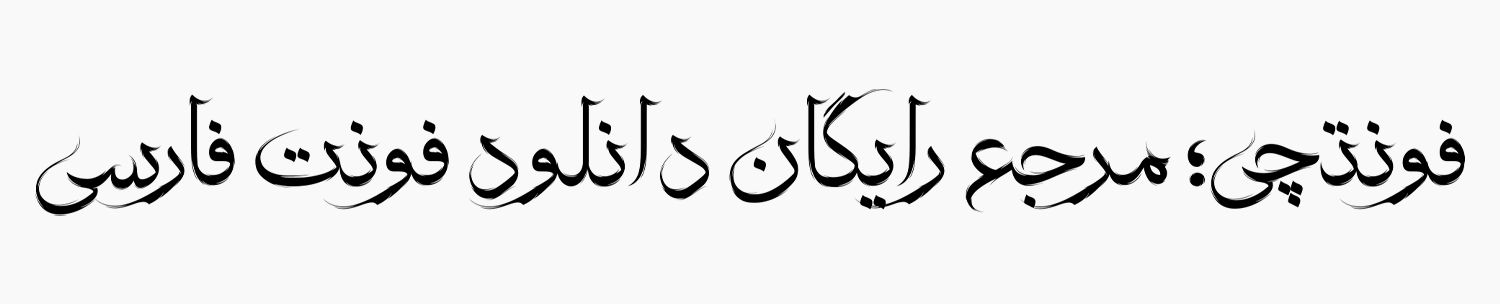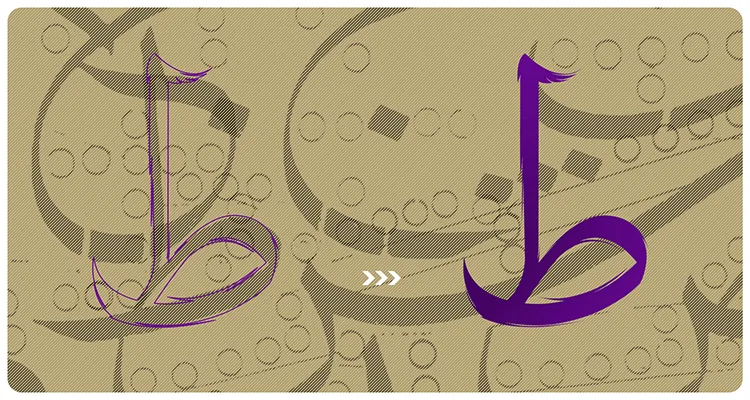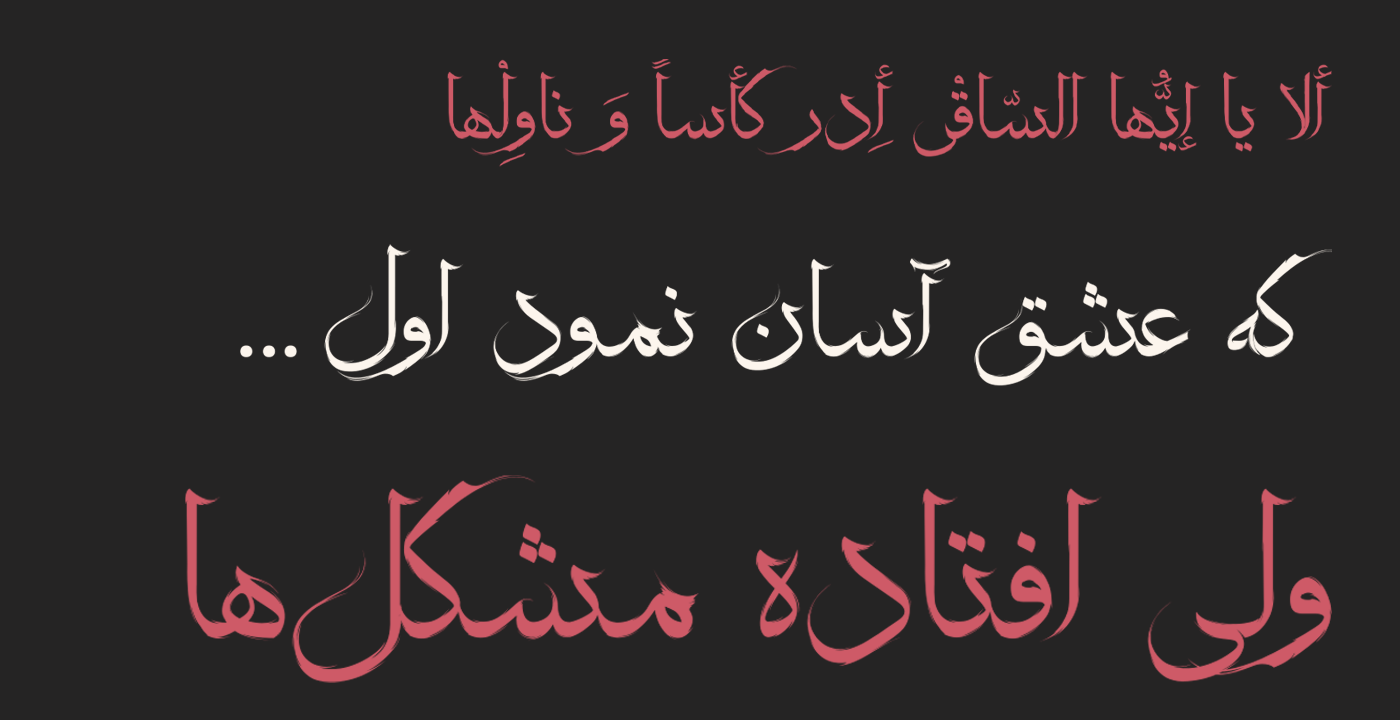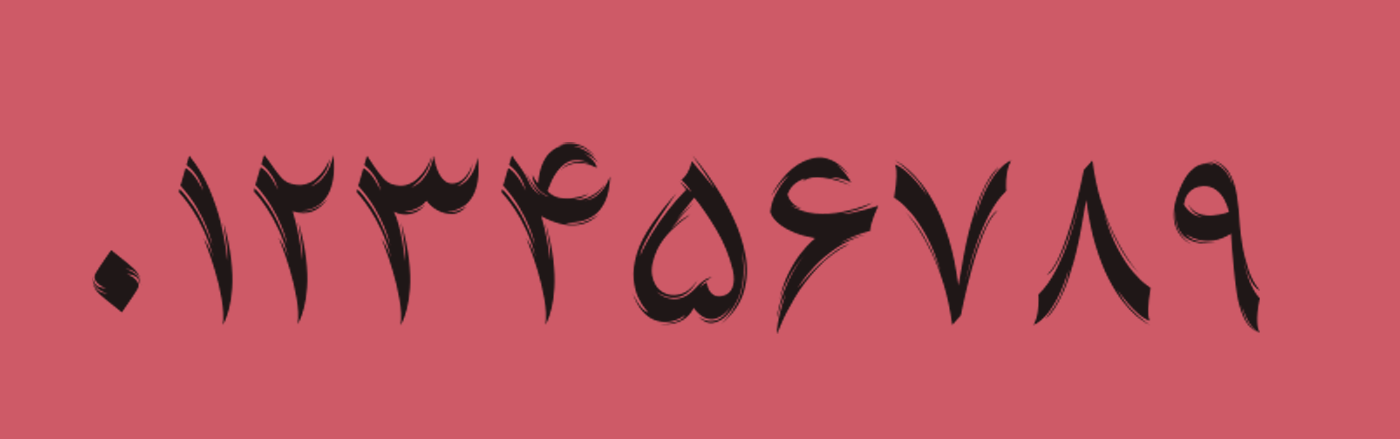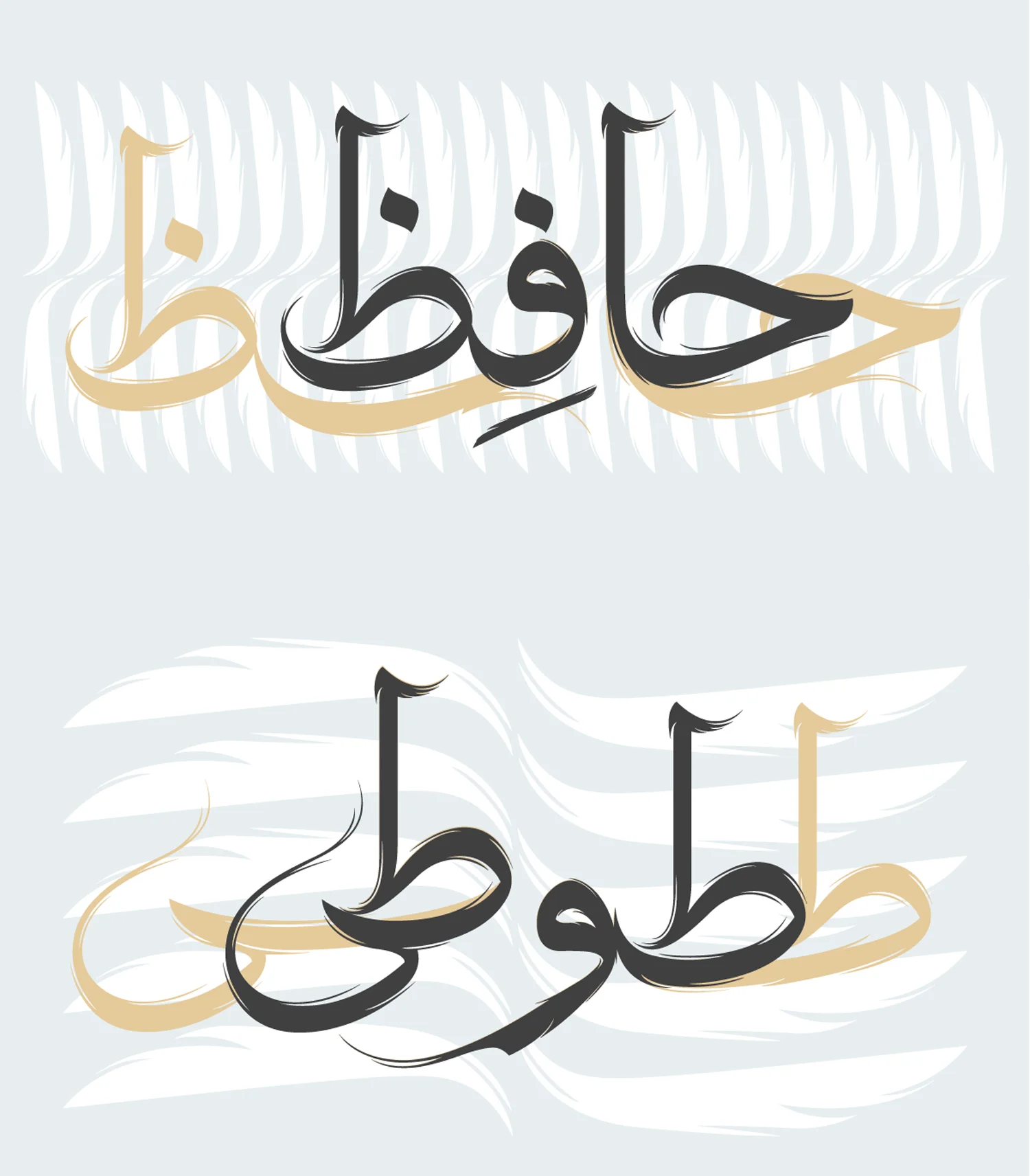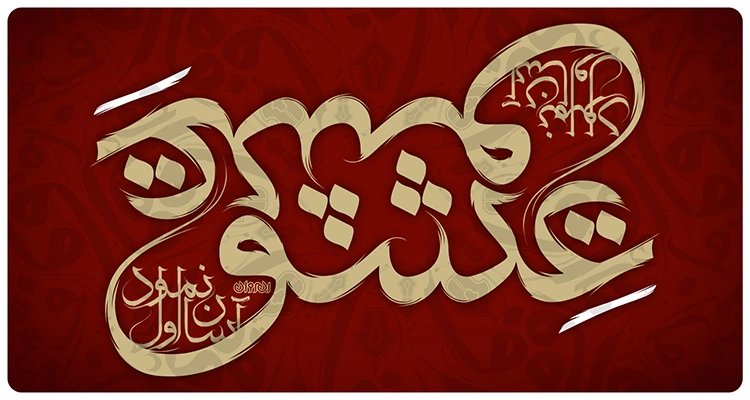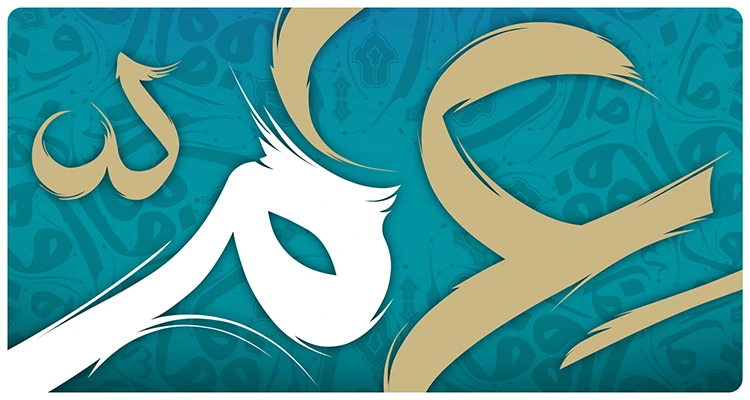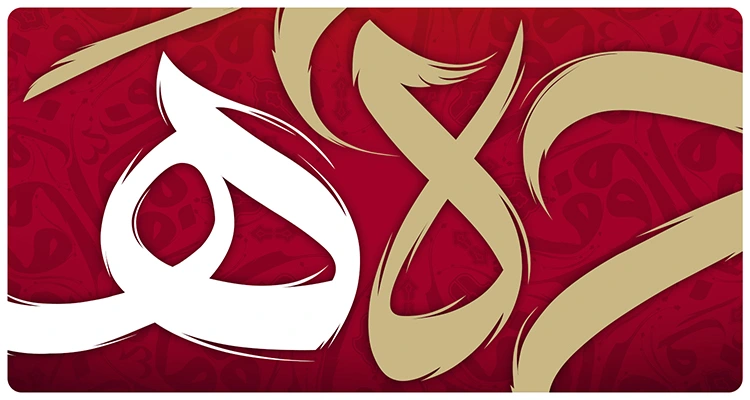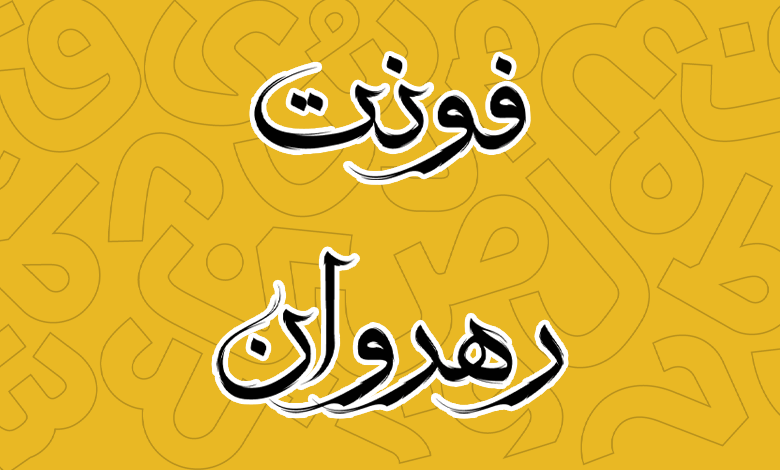
فونت رهروان (Rahrovan)
فونت رهروان (به انگلیسی: Rahrovan) در سبک فونت خوشنویسی تزئینی و بر پایه خط ثلث طراحی شده است که از دو زبان فارسی و عربی پشتیبانی میکند. از این قلم میتوان برای کارهای گرافیکی، تزئینی و تبلیغاتی که درونمایه فرهنگی و هنری دارند استفاده کرد.
طراحی این قلم توسط ابوالفضل رهروان صورت گرفته است که خود در کارهای گرافیکی از این سبک قلم استفاده میکرد تا اینکه به فکر ساخت این قلم بر پایه فونت نرمافزاری افتاد تا عرضه عمومی شود و برای همگان در دسترس باشد.
در ادامه این نوشته از سایت فونتچی به نقد و بررسی کامل فونت رهروان خواهیم پرداخت؛ قلمی با سبک خط نسخ که بر پایه خط ثلث ساخته شده و درون مایهای خوشنویسی دارد. با توجه به امکاناتی که این قلم دارد میتوانید از آن برای کارهای گرافیکی خلاقانه به کمک حروف جایگزین و گلیفهای تزئینی موجود استفاده کنید.
بررسی و دانلود فونت (Rahrovan)
طراحی حروف در قلم رهروان معمولا خارج از سیستم و قواعد فونتهای مرسوم به یکدیگر متصل شدهاند و بیشتر بر اساس خلاقیت شخصی طراح ترکیبات ایجاد شده است.
فونت رهروان بر پایهی خط ثلث طراحی شده و سعی شده با حفظ روحیه خوشنویسی، فضای بصری جدیدی از این خوشنویسی اصیل به نمایش درآید.
نتیجه کار فونتی رها و هماهنگ است که میتوان بهوسیله آن تایپوگرافیهای جذاب و متفاوتی ایجاد کرد.
فرمهای رها و خطوط ظریف در ترکیب با بدنهی حروف باعث میشود کاربرد این فونت در ابعاد بزرگ، جلوهای ویژه و منحصر به فرد را نمایش دهد.
ابوالفضل رهروان؛ طراح قلم رهروان.
اگر به دنبال قلمی برای کارهای خوشنویسی هستید که پایبند به اصول نباشد و تا حدی طراحی آزاد و رها داشته باشد، تا پایان با ما همراه باشید.
سبک طراحی و وزن فونت رهروان
در قلم خوشنویسی رهروان این امکان وجود دارد که بتوانید حروف را کشیده کنید یا اینکه به کمک ترکیبات و گلیفهای تزئینی موجود در آن، ساختار کلمات را بهطور کلی تغییر دهید تا آثاری خلاقانه به نمایش بگذارید.
در این قلم خطوط عمودی دارای یک طره تزئینی و پرچمگونه هستند که ساختاری مشابه پر به خود گرفتهاند. شاید در نگاه اول با دیدن حروفی مثل «الف، د، ذ، ط، ظ، ل» فکر کنید که با یک قلم عاشورایی مواجه هستید.
یا در حروف دیگری مانند «ک، گ، ل، و، ی» که دارای خطوط کشیده در جهت افقی یا مورب در ابتدا یا انتهای حروف هستند، یک طره تزئینی دیگر نیز به چشم میخورد که ساختاری کشیده داشته و هرچه کشیدهتر میشود ضمن تغییر جزئی ضخامت، یک ساختار انهایی نیز در آن شکل میگیرد.
پشتیبانی از دو زبان فارسی و عربی
فونت رهروان از دو زبان فارسی و عربی پشتیبانی میکند که برای هر دو زبان پیش از هر چیز حروف مشترک پیادهسازی شده است. زبان عربی هم که بر پایه رسمخط فارسی است تمامی این نقاط مشترک را با خود به همراه دارد.
اما افزون بر این برخی حروف که با اتصال به گلیفهایی ساختار کشیده به خود خواهند گرفت برای هر دو زبان در نظر گرفته شده است تا ساختاری خلاقانه را برای ایجاد طرحهای متنوع در اختیارتان قرار دهد.
اعراب نیز در این فونت با یک همنشینی خاصی در کنار هم قرار میگیرند. مثلا زمانی که از اعراب «تشدید همراه با سایر اعراب» استفاده میکنید، با یک شکل خاصی روی هم قرار میگیرند که به زیباتر کردن متون کمک میکند.
این قلم هرچه در ابعاد بزرگتر استفاده شود، زیبایی خود را بیشتر نمایان خواهد کرد که به همین جهت برای استفاده در فونت عناوین، شعارهای تبلیغاتی و کارهای فرهنگی و هنری بسیار موثر است.
ویژگی دیگر فونت پشتیبانی از اعداد فارسی است که با همان سبک نسبتا هاشور خورده ایجاد شده است. تمامی حروف نیز همان ساختار خوشنویسی مرکب و قلم را در خود دارند.
اما یک نکته منفی که در این خصوص برای زبانی عربی وجود دارد، عدم پشتیبانی از تایپ اعداد «۴۵۶» با این ظاهر در این زبان است. اگر قرار باشد برای زبان عربی از اعداد استفاده کنید، این ۳ عدد تایپ اعداد فارسی را خواهند داشت.
دارای ترکیبات و حروف جایگزین
این قلم از ترکیبات و حروف جایگزین متعدد پشتیبانی میکند که به زیباتر کردن متون کمک خواهد کرد. متداولترین حروف جایگزین فونت رهروان شامل «ک، گ، ع، غ، ه، ی، س، ش» هستند که در همه فونتها تقریبا چنین حروفی را میبینیم.
نوع دیگر این حروف به صورت ترکیبات استفاده شده هستند که با قرار گیری در ابتدا، میانه یا انتهای همان حروف ذکر شده، تایپ خاصی از کلمات را در اختیار قرار میدهند.
دارای گلیف های تزئینی متنوع
این قلم از گلیفهای تزئینی متعددی که در زبانهای کردی و اردو بیشتر آنها را میبینیم نیز پشتیبانی میکند که همین ویژگی باعث شده تا حدودی پشتیبانی از این دو زبان را هم به این دلیل که دارای رسم خط فارسی است داشته باشد.
اما بهطور قطع نمیتوان ادعا کرد که پشتیبانی کاملی دارد؛ مثلا در زبان اردو حروف «ـه، ـهـ، ـه، ـی» دارای ساختاری کاملا متفاوت از زبان فارسی هستند که در این قلم صرفا حالتهای «ﮧ، ے» قابل استفاده است.
مناسب کارهای خوشنویسی و گرافیک تزئینی
از این قلم میتوانید به شکل خلاقانه برای ایجاد کارهای خوشنویسی و تزئینی استفاده کنید که میتواند در حوزههای مختلف فرهنگی و هنری، تبلیغات، شبکههای اجتماعی و… مورد استفاده قرار گیرد که در زیر نمونههایی از آن را نیز مشاهده میکنید.
اینکه از این قلم چه استفادههای دیگری داشته باشید، کاملا به ذهن خلاق شما وابسته است. چرا که خوشنویسی خود هنری است که با خلاقیت به خرج دادن، بیشتر خود را نمایان خواهد نمود. خصوصا زمانی که پای یک قلم نرمافزاری در میان باشد.